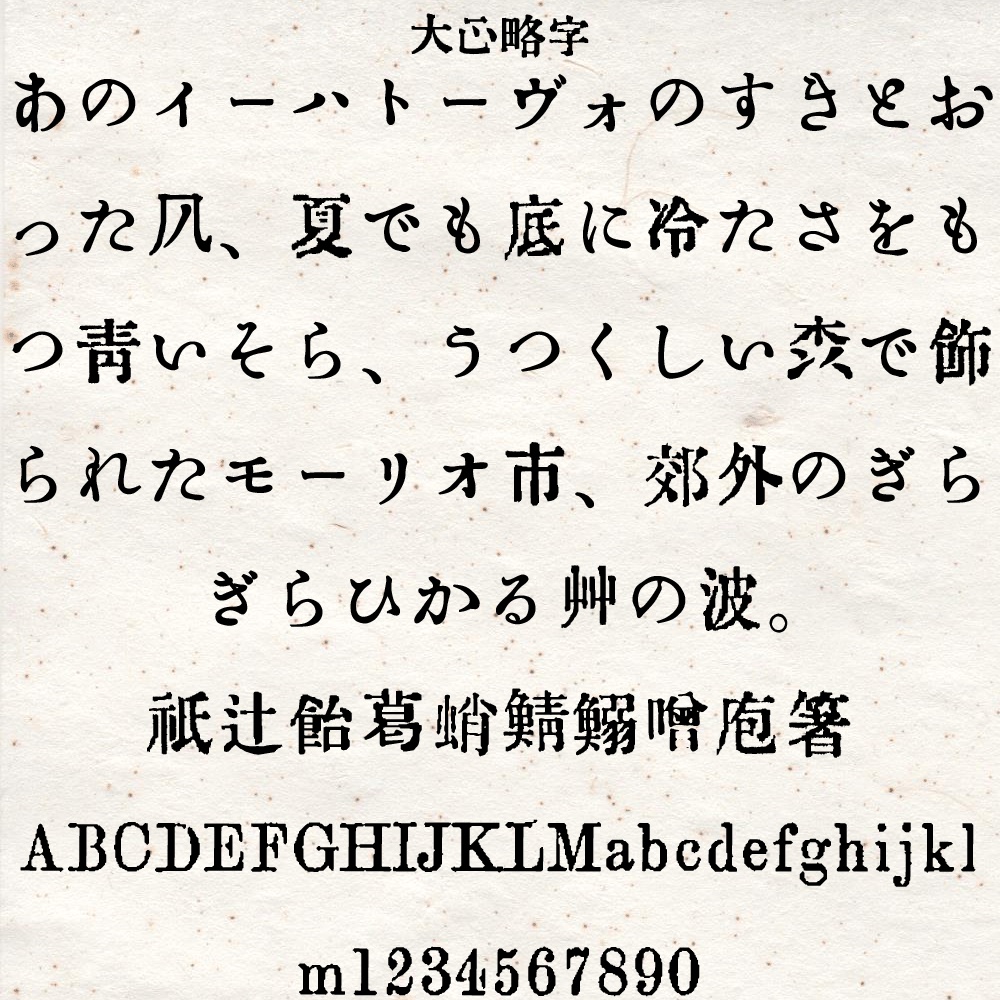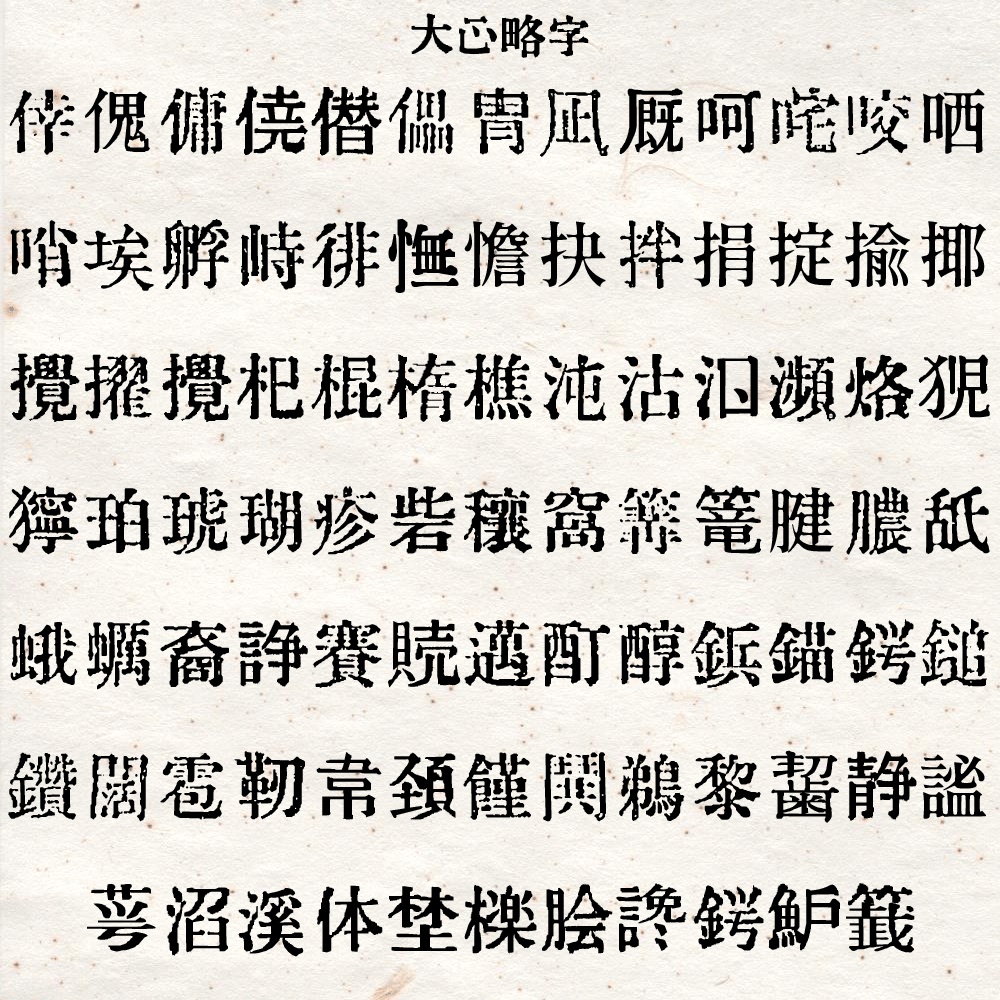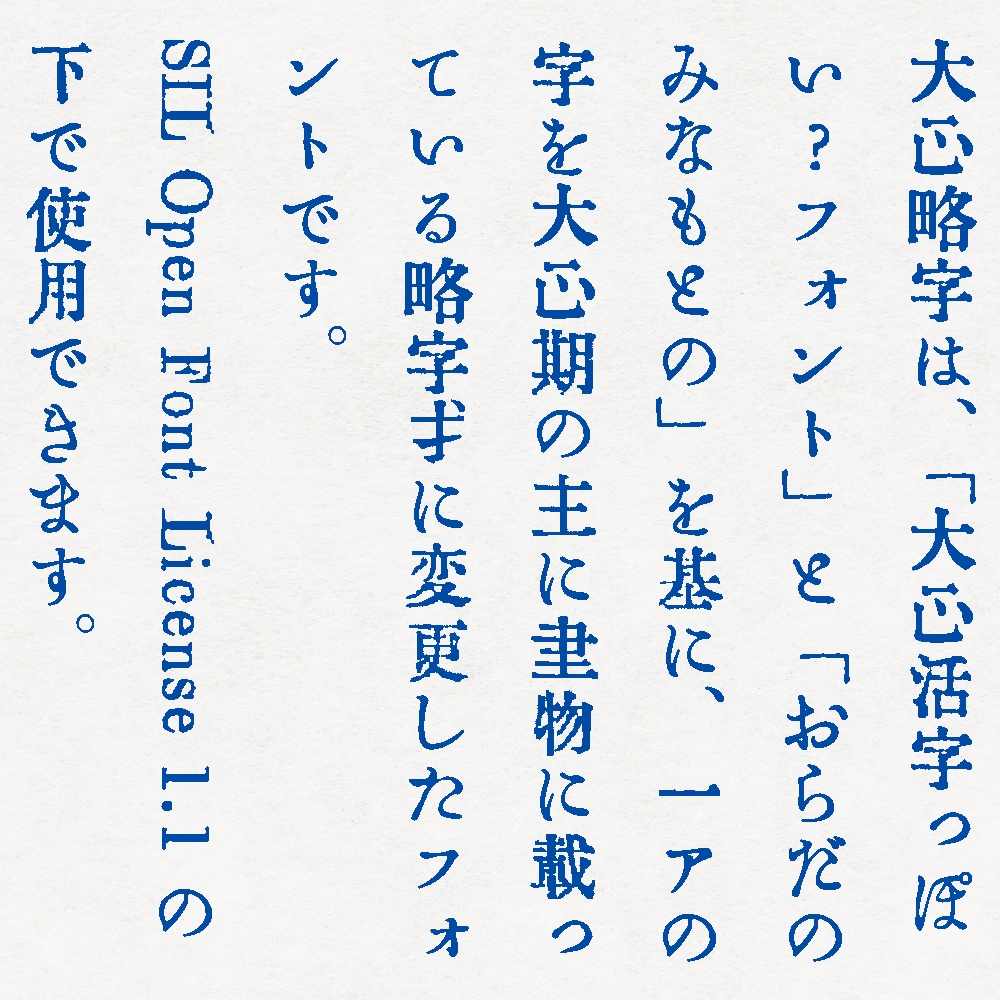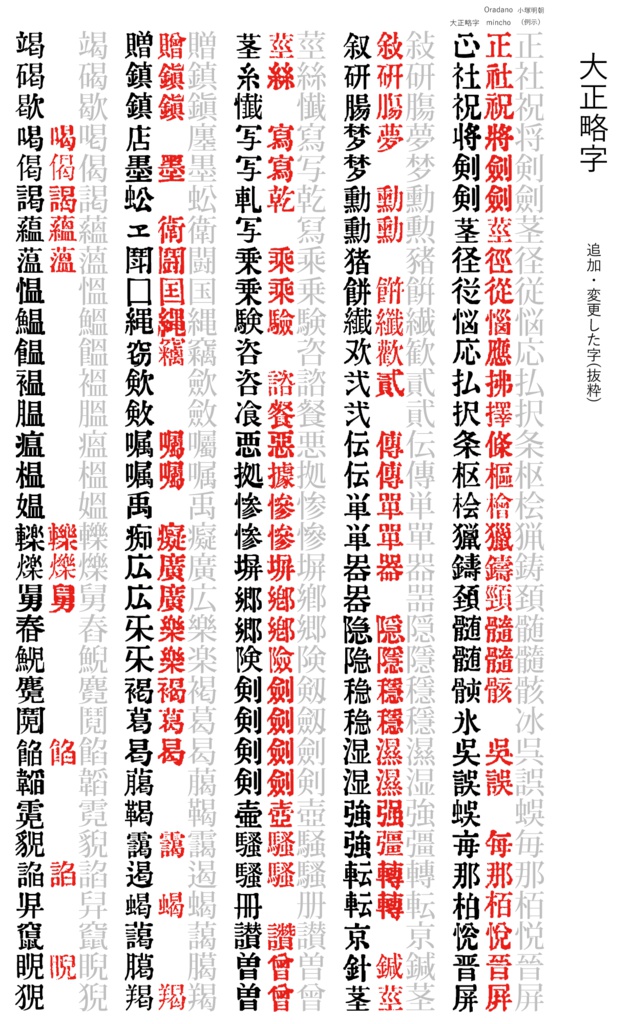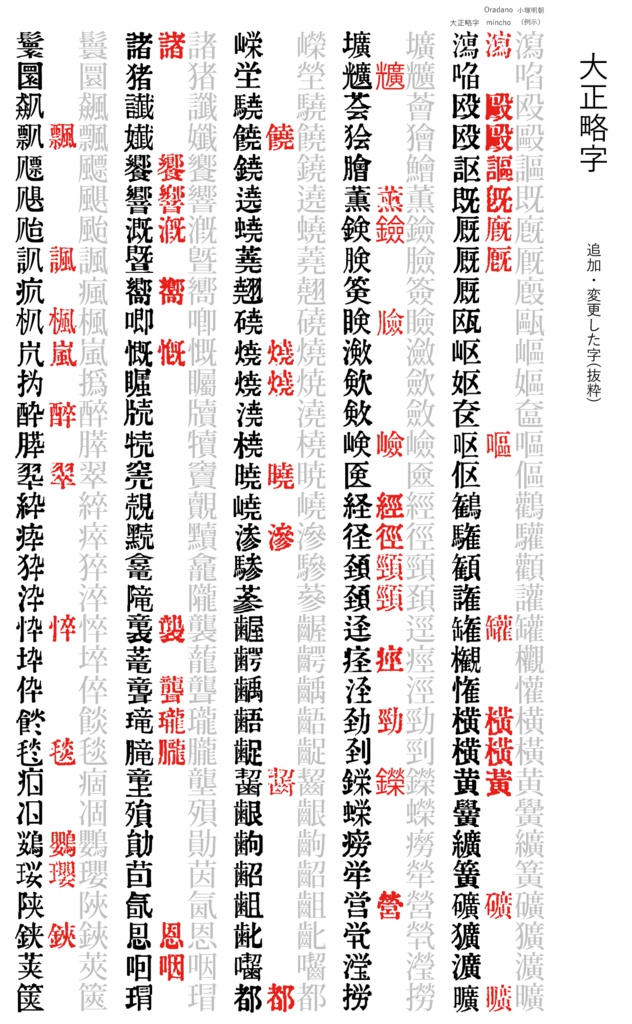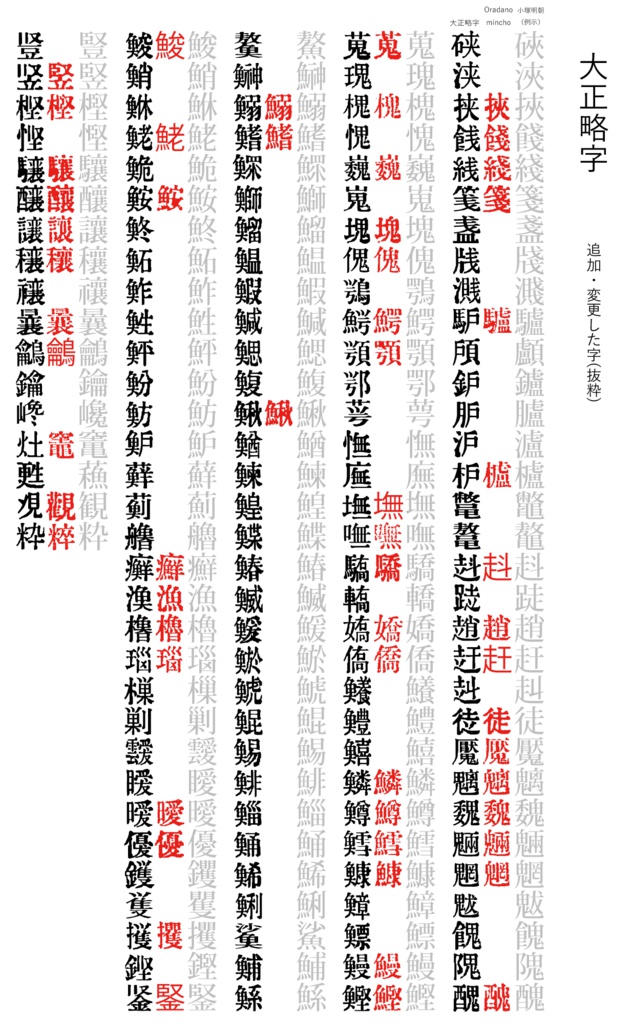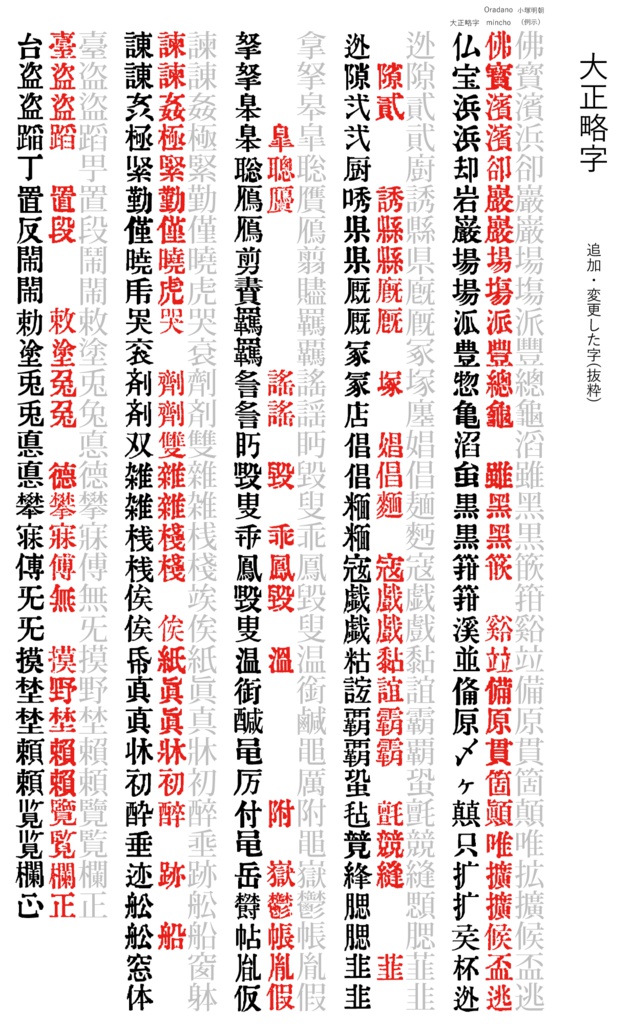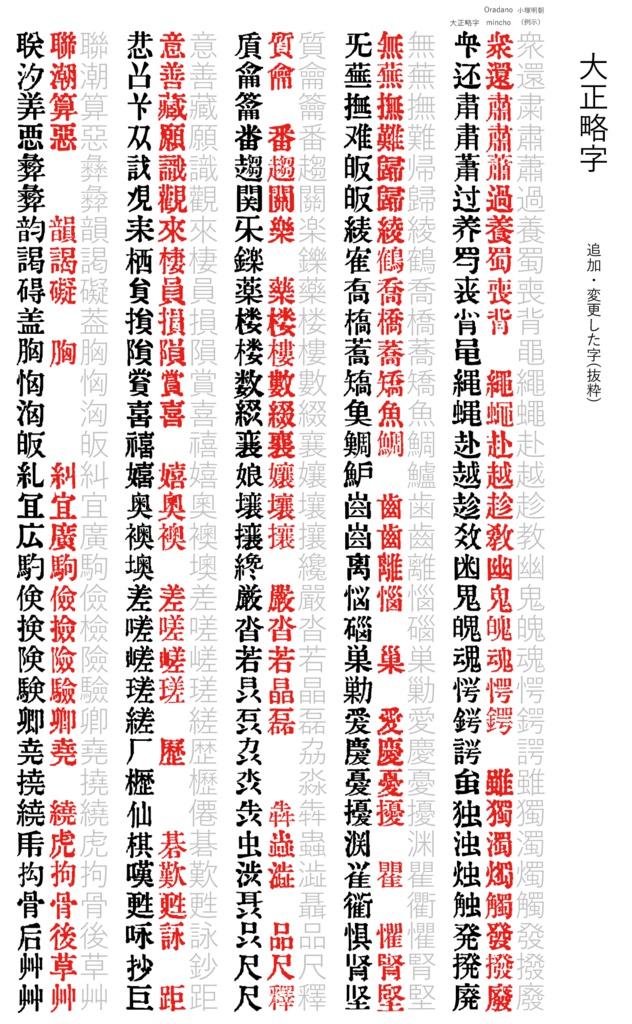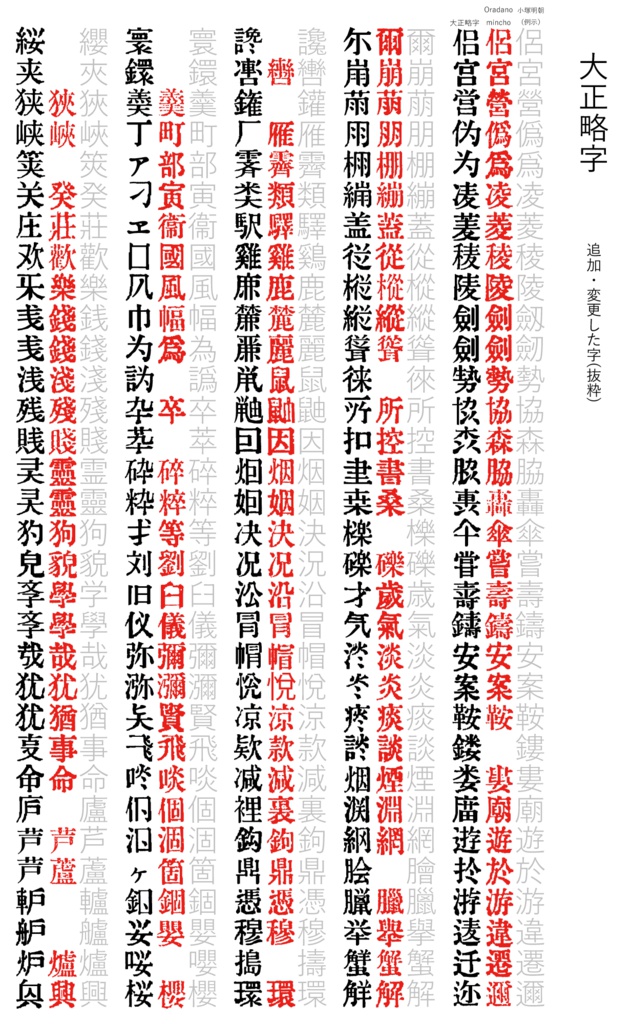
大正略字フォント
大正略字は、「大正活字っぽい?フォント」(https://nukosuki.booth.pm/items/737294)と「おらだのみなもとの」(https://nukosuki.booth.pm/items/739390)を基に、一部の字を大正期の主に書物に載っている略字等に変更したフォントです。 SIL Open Font License 1.1の下で使用できます。 参考:文部省『漢字整理案』、玉井米南『漢字摘要』、鈴木周作『実用音引作文辞典』、常用漢字表(大正12年)、後藤朝太郎『文字の沿革』、下中芳岳『や此は便利だ! : ポケツト顧問』、陸軍中央幼年学校『用字便覧』, 千葉県立大多喜中学校第一部会『国語漢文便覧』, 大川重吉, 神田英作『国語教授の根柢』, 山口県室積師範学校『国語要覧』、島根県女子師範学校附属小学校『初等教育重要問題の研究.第2巻』、村本猶太郎『中等国語漢文提要』、「婦人世界」、石碑 SIL Open Font License 1.1日本語訳:https://licenses.opensource.jp/OFL-1.1/OFL-1.1.html 元フォント様: 梅フォントhttps://ja.osdn.net/projects/ume-font/wiki/FrontPage 源雲明朝https://github.com/ButTaiwan/genwan-font/ Oradano明朝http://www.asahi-net.or.jp/~sd5a-ucd/freefonts/Oradano-Mincho/ GL-築地5号https://gutenberg.osdn.jp/font/ja.html#Japanese むつきhttp://mandel59.github.io/mutsuki/ @gata. Gutenberg Labo. Ryusei Yamaguchi. HORAI Wataru. modified font of Source Han Serif. ButTaiwan 予約フォント名:大正略字